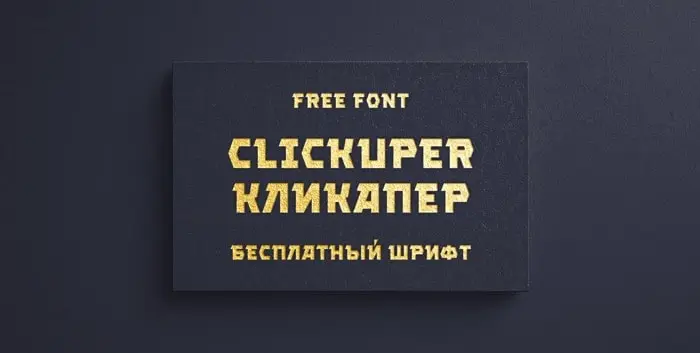
A Clickuper Display Font é uma fonte geométrica que traz um toque retro-futurista e moderno para qualquer projeto. Sua simplicidade geométrica a torna perfeita para aplicações como logotipos, cartões de convite, embalagens ou qualquer outro tipo de material publicitário formal. Ela foi projetada para ser usada em ambientes onde um design minimalista e moderno é desejado, seja para materiais educacionais como livros e revistas ou até mesmo itens pessoais como cartões de aniversário, embalagens de cosméticos ou maquiagem, bem como produtos de moda. Essa fonte exala elegância e simplicidade, tornando-se a escolha ideal quando você busca um toque moderno sem comprometer a estética clássica. Sua versatilidade permite que seja utilizada em diversos contextos, fazendo-a uma opção popular entre designers de gráficos.